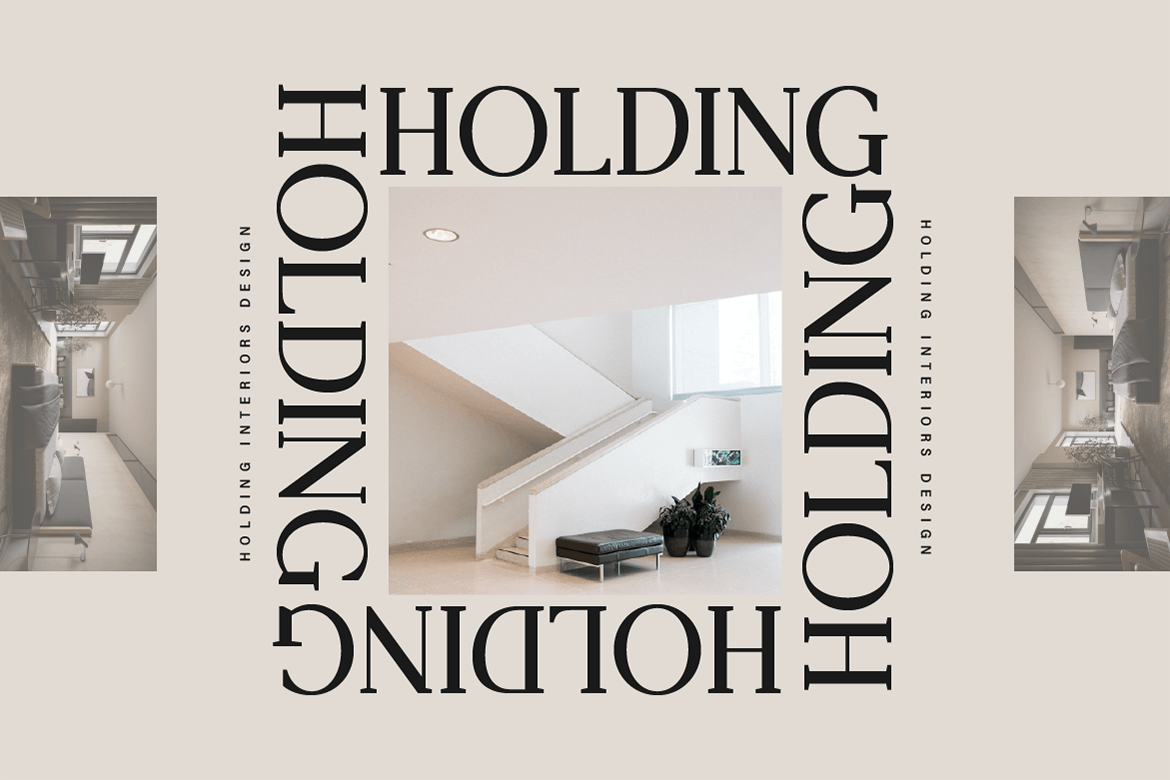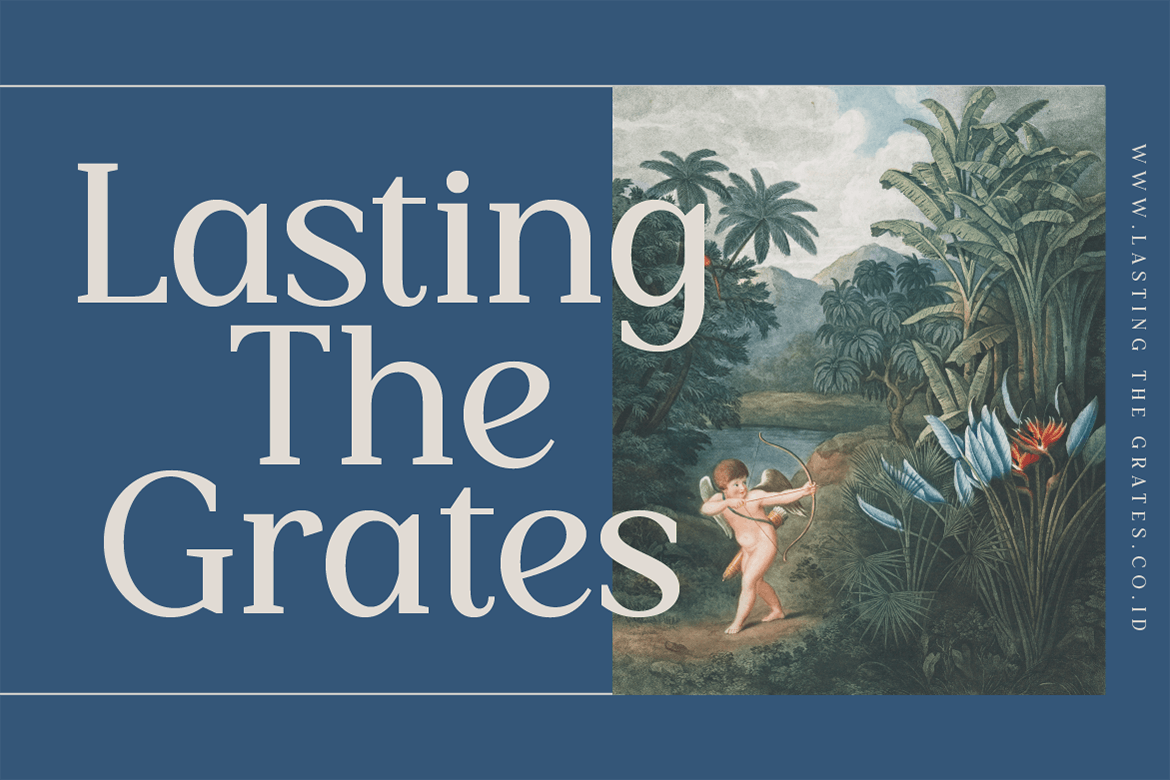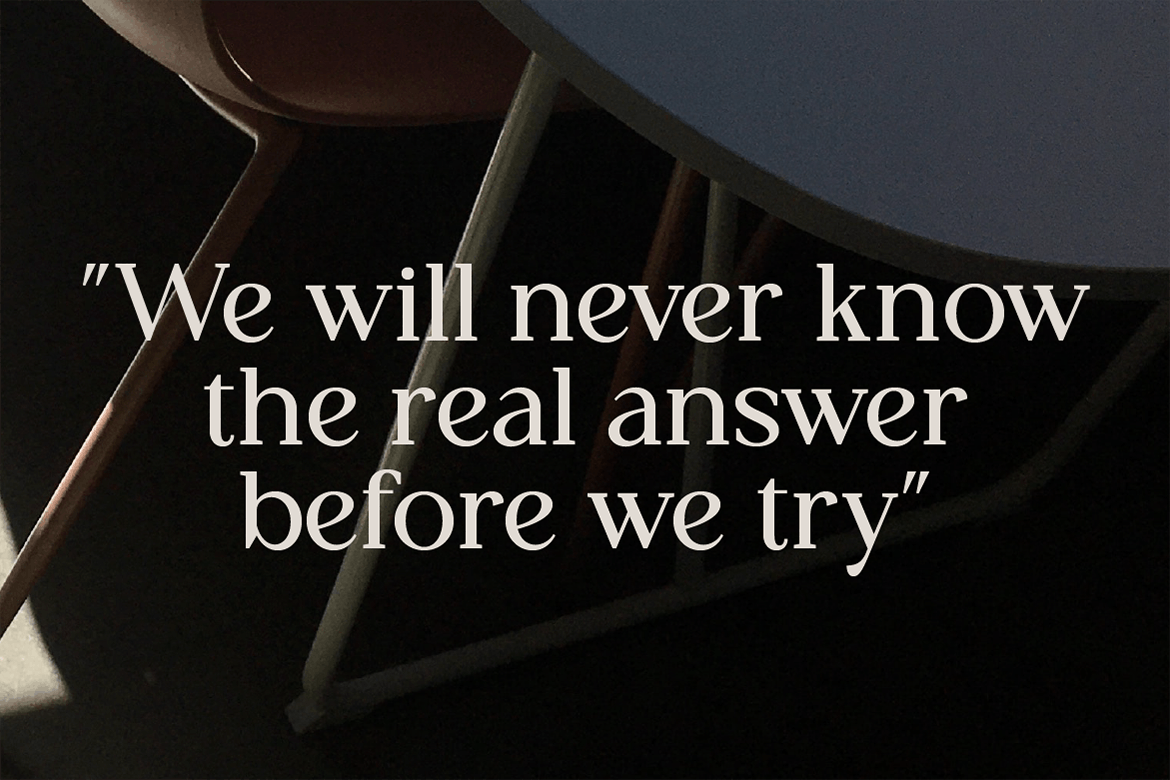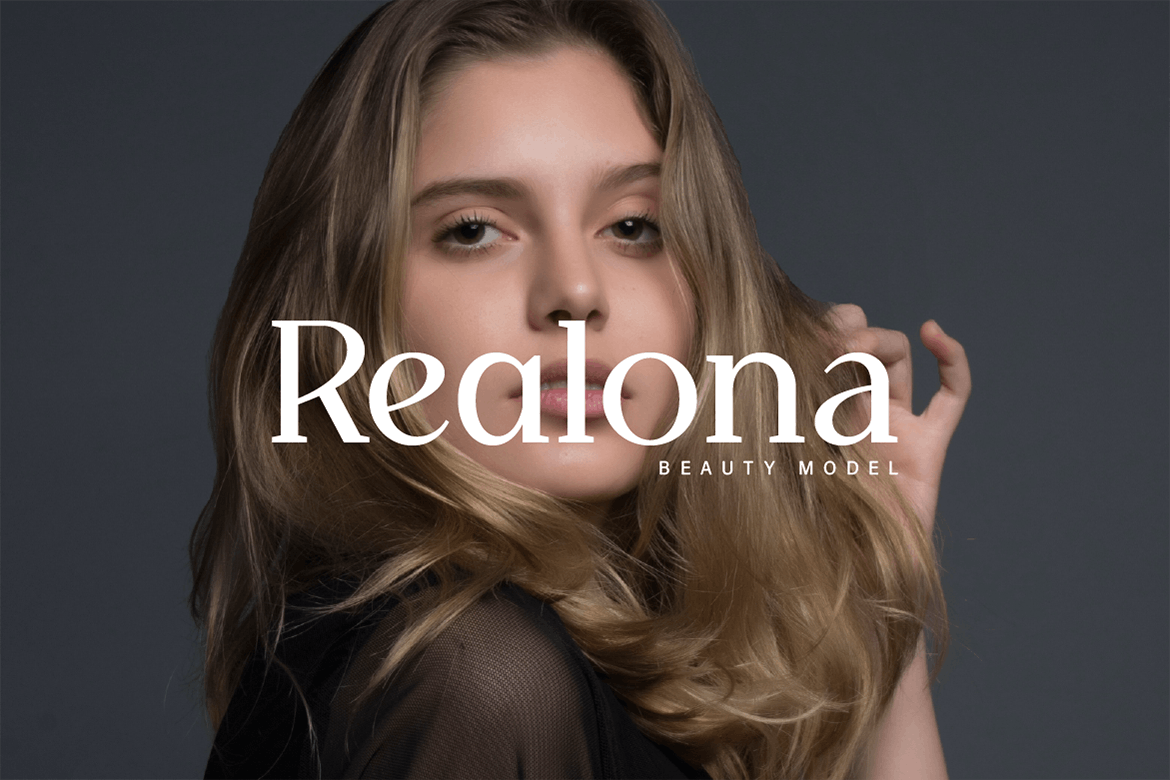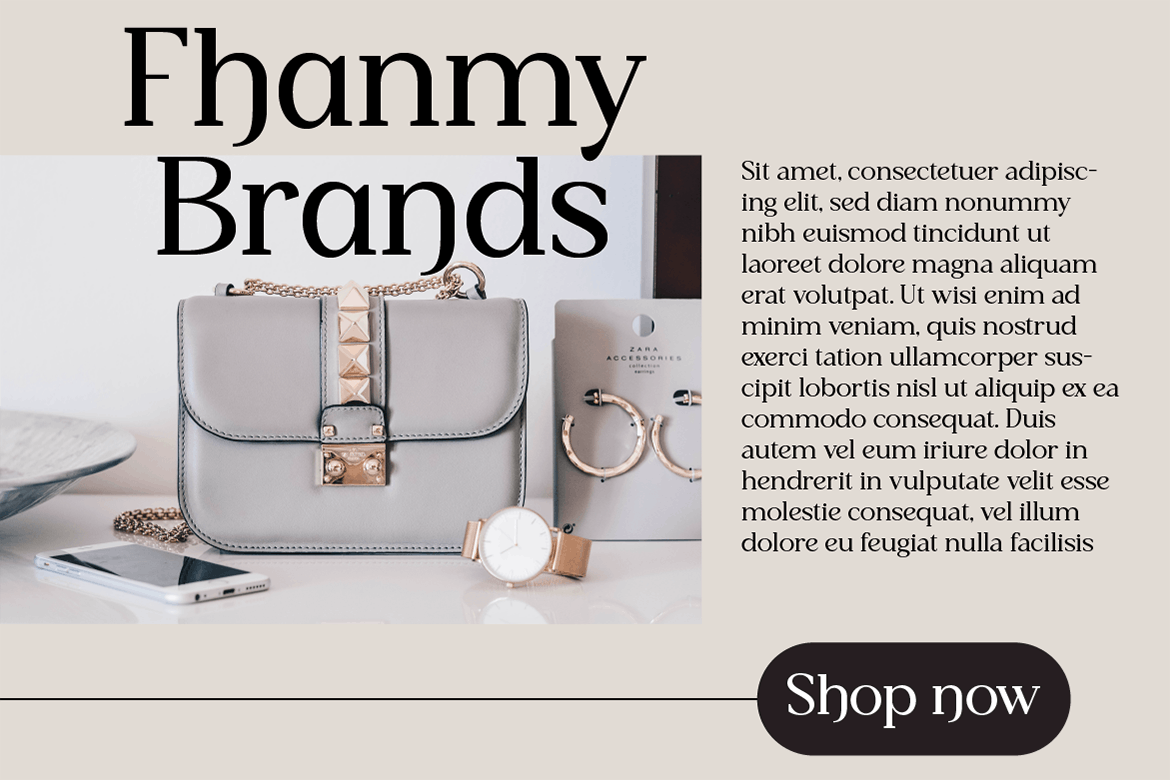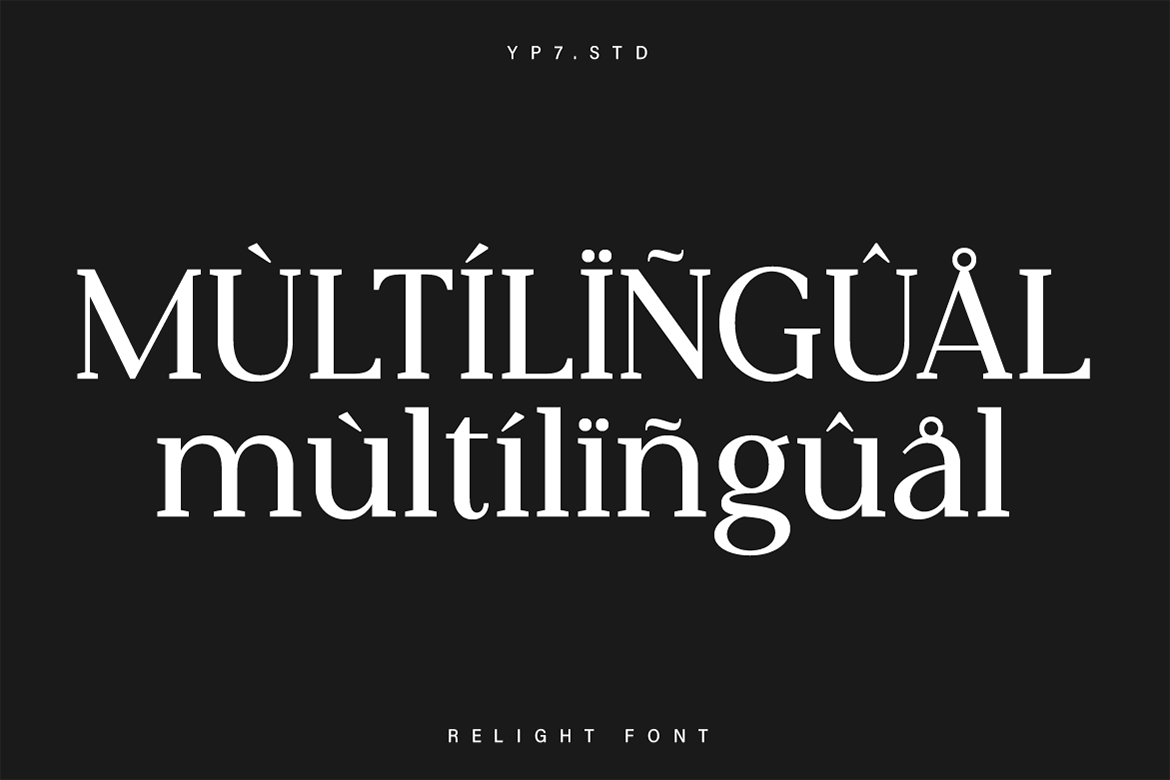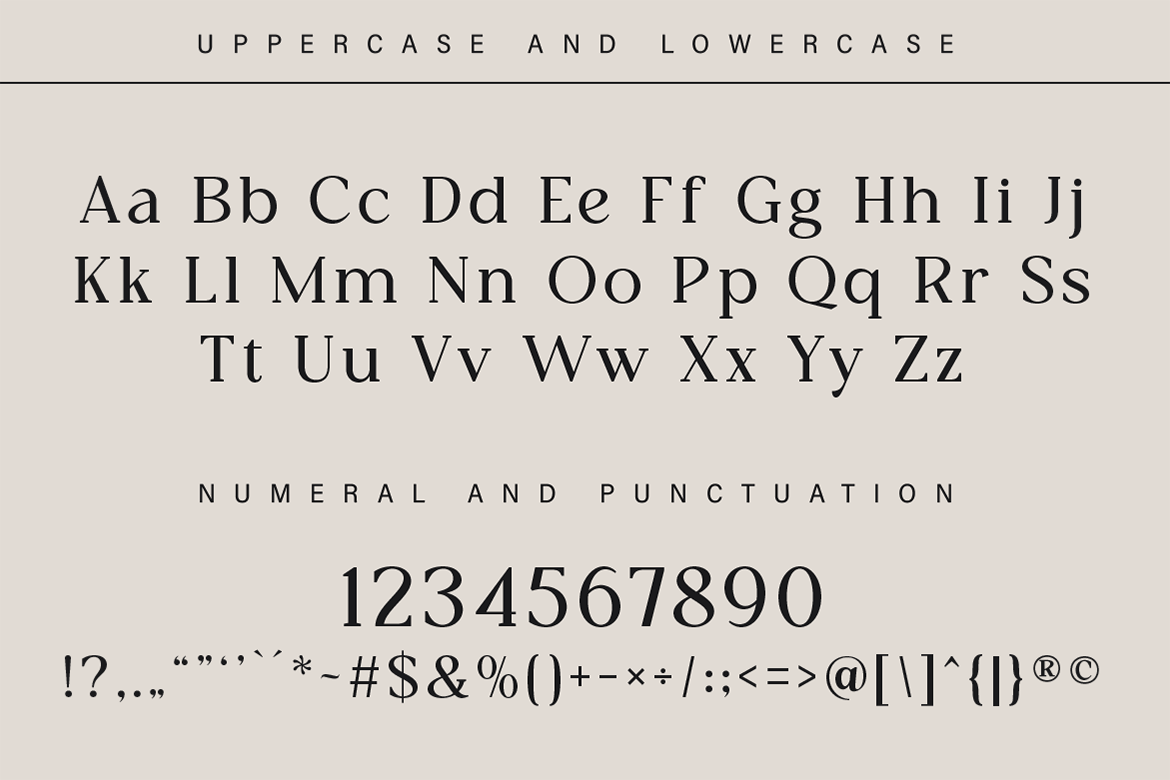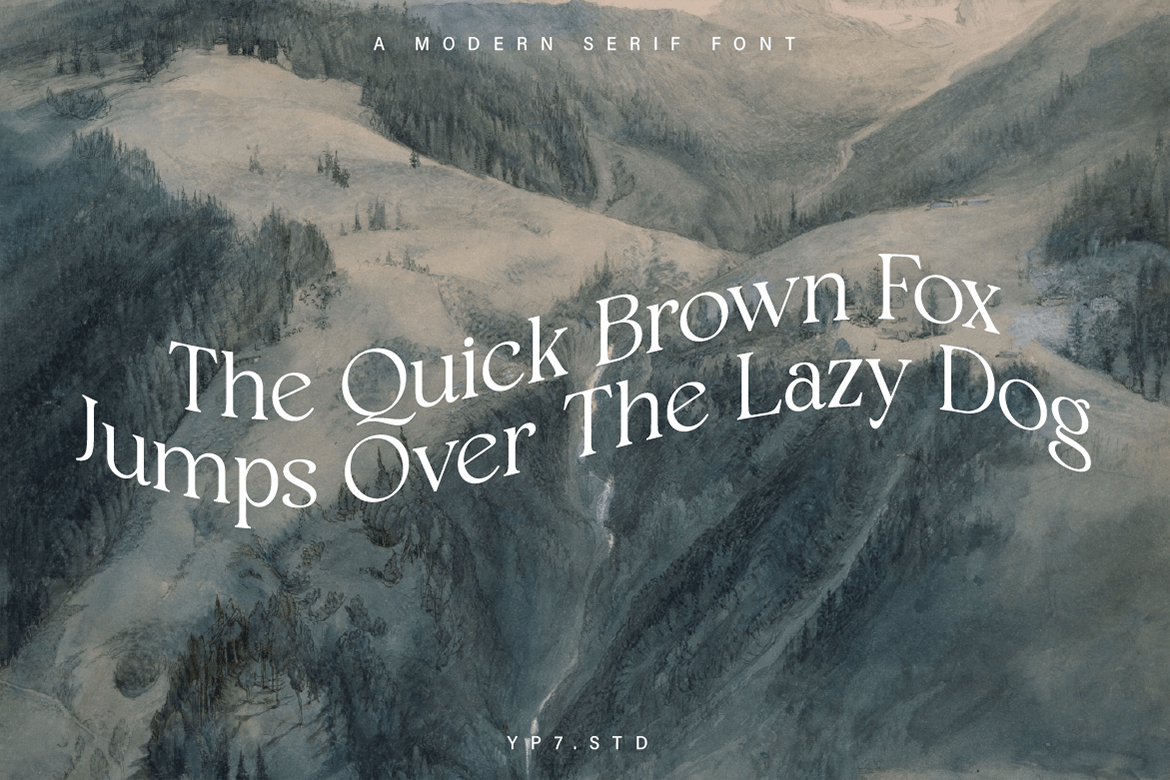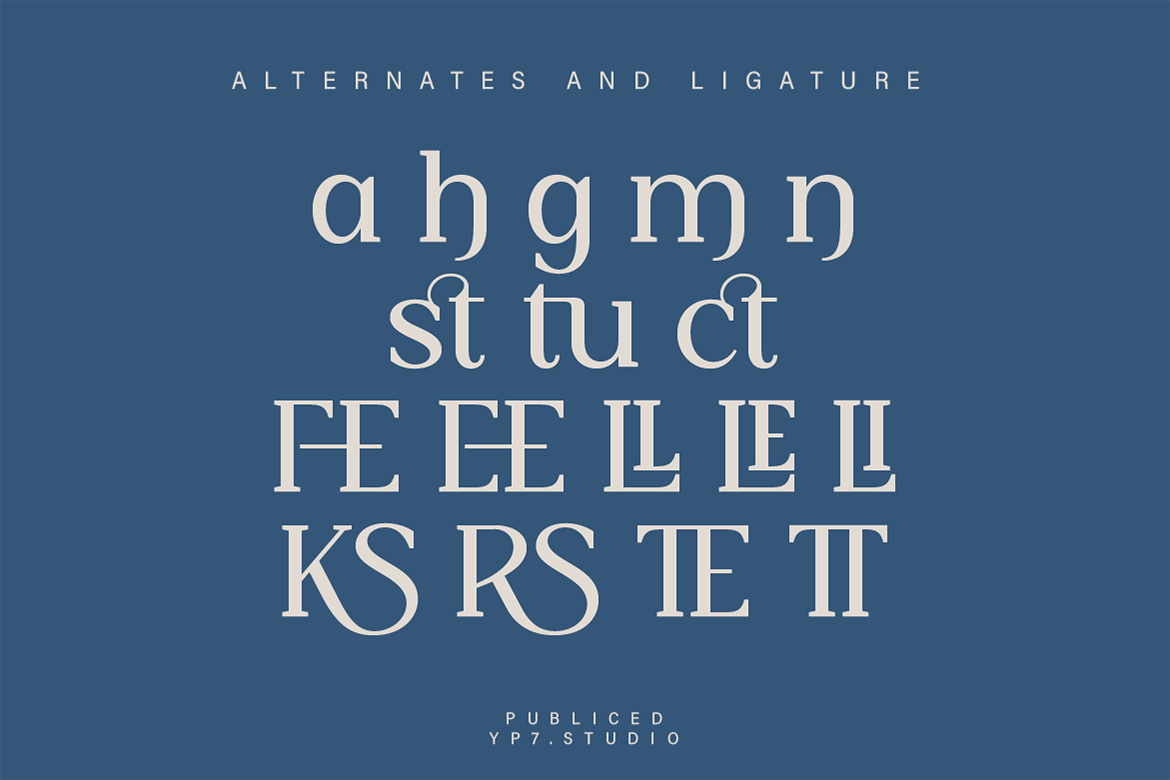
دانلود فونت مدرن سریف Relight برای طراحی
Modern Serif Font
فونت سریف مدرن Relight را دانلود کنید و پروژه‌های خود را زیباتر کنید.
فونت مدرن سریف Relight یک انتخاب عالی برای طراحان است که به دنبال زیبایی و خوانایی در پروژه‌های خود هستند.